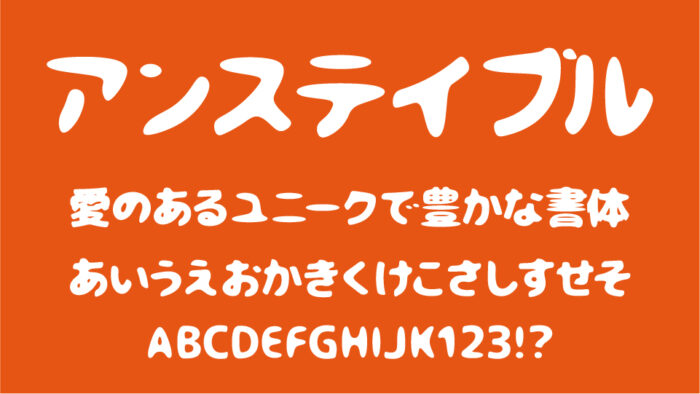
アンステイブル・ゴシック
アンステイブル・ゴシックフォントは、丸みを帯びつつ不安感のある、太めのデザインフォントです。
丸みとぽってりとした形状が特徴的で、文字が溶けて出してしまったような質感があり、不安感を感じながらも、柔らかくも優しい印象をもつユニークなフォントです。
収録文字は、漢字(5,000文字以上)・ひらがな・カタカナ・アルファベット・数字・記号が収録されています。